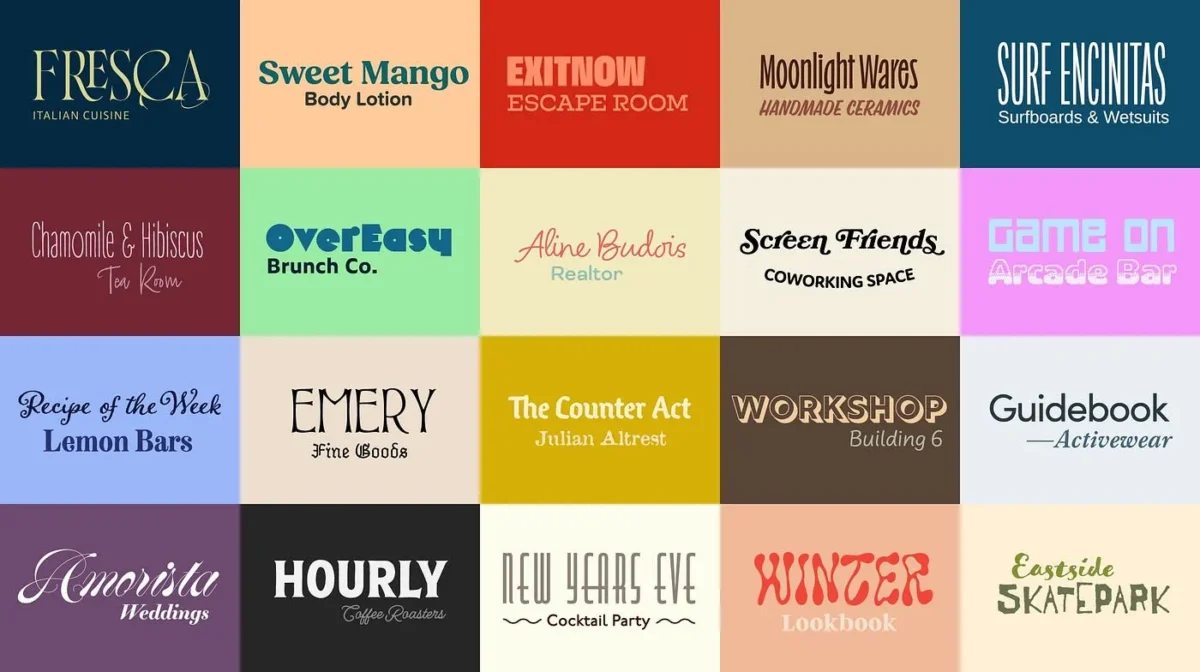
Один удачно подобранный шрифт способен задать настроение всему макету. Но в реальных проектах одного шрифта почти всегда мало: нужен контраст между заголовком и текстом, между главным и второстепенным. Здесь и начинается работа со шрифтовыми парами — искусством сочетать шрифты так, чтобы они усиливали друг друга, а не спорили.
Шрифтовая пара — это два (реже три) шрифта, которые используются в одном проекте и хорошо работают вместе. Обычно один отвечает за заголовки, второй — за основной текст. Задача пары не в том, чтобы шрифты были похожими, а в том, чтобы они дополняли друг друга и создавали понятную иерархию.
Грамотная пара делает макет выразительным и при этом читаемым. Неудачная — превращает страницу в визуальный шум, где элементы конкурируют за внимание.
В основе хорошей пары лежит баланс между двумя силами.
Контраст не даёт шрифтам сливаться. Если они слишком похожи, возникает ощущение ошибки — будто хотели один шрифт, но что-то сбилось. Контраст создают за счёт начертания, насыщенности, пропорций или характера шрифта.
Единство удерживает пару вместе. У шрифтов должно быть что-то общее — настроение, эпоха, пропорции, — иначе они выглядят случайным набором.
Идеальная пара — это заметный контраст при скрытом родстве.
Антиква и гротеск. Самый надёжный приём: шрифт с засечками в паре со шрифтом без засечек. Они достаточно разные по природе, но прекрасно уживаются. Классика — гротеск в заголовке и антиква в тексте или наоборот.
Контраст по насыщенности. Один и тот же шрифт в жирном начертании для заголовка и в обычном для текста. Простой и почти беспроигрышный вариант.
Шрифты одного семейства (суперсемейства). Некоторые гарнитуры выпускают сразу в нескольких вариантах — с засечками и без. Они изначально созданы для совместной работы и гарантированно сочетаются.
Контраст по характеру. Декоративный, выразительный шрифт для заголовка и спокойный нейтральный для текста. Акцент берёт на себя заголовок, а текст не мешает чтению.
Шрифтовая пара — это маленький, но мощный инструмент: правильное сочетание делает дизайн выразительным, структурированным и удобным для чтения. В основе всегда лежит один принцип — заметный контраст при внутреннем родстве. Освоив его, дизайнер перестаёт подбирать шрифты наугад и начинает выстраивать осознанную типографику, которая работает на бренд и на читателя.